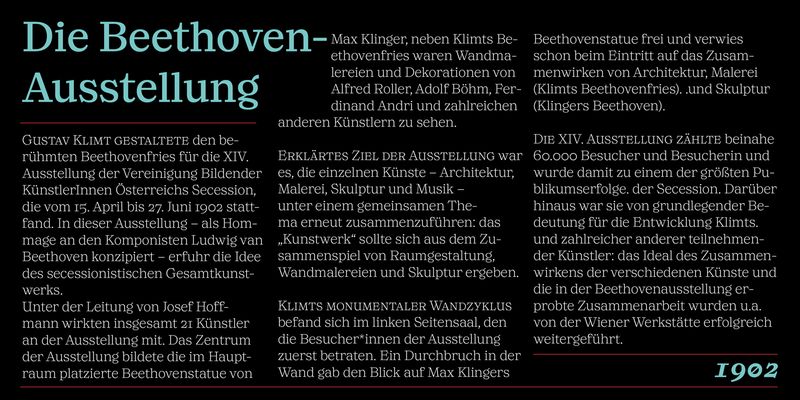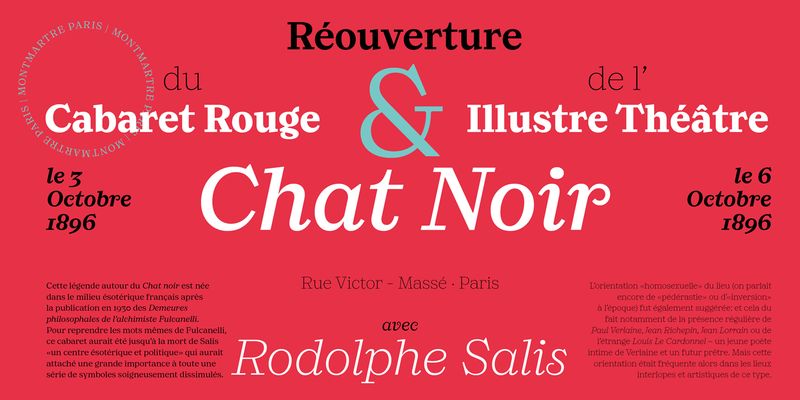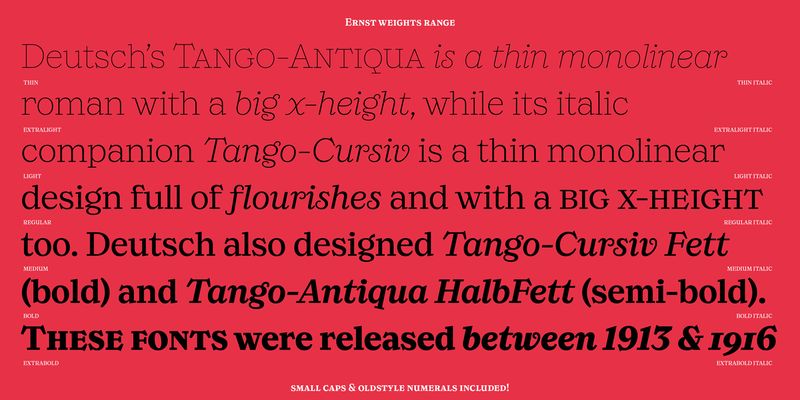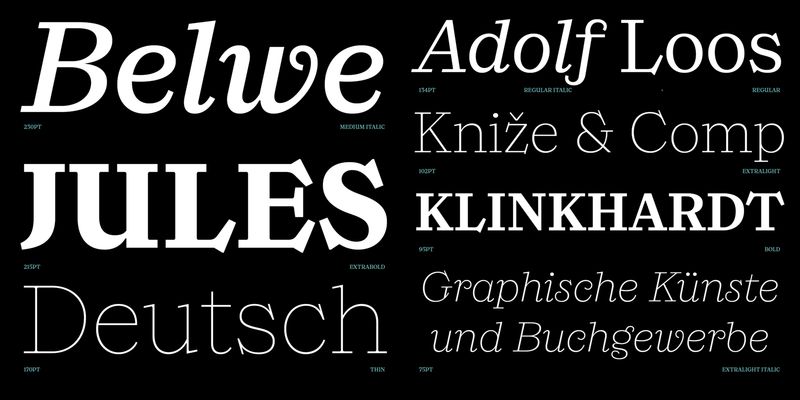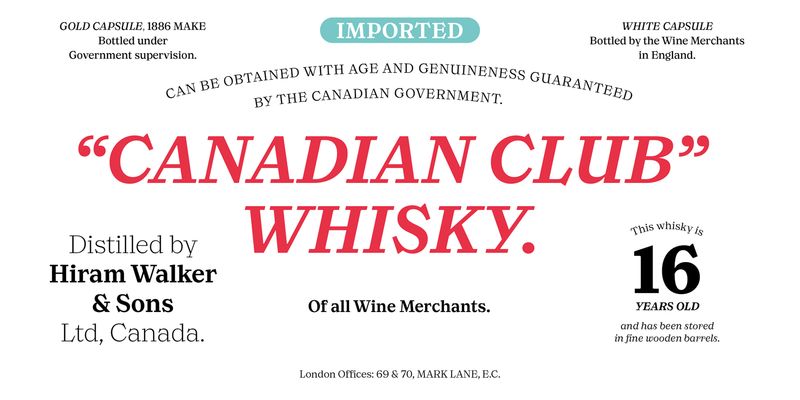
Ernst ist eine elegante, aber verspielte serifenbetonte Schrift, die an einige eigentümliche Schriften des frühen 20. Jahrhunderts erinnert, aber durch ihre breite Anwendungspalette auf zeitgenössische Anforderungen eingeht. Ernst ist weniger ein Revival, sondern verbindet Schriftdetails von Avantgarde-Schriften wie Ernst Deutsch/Drydens Tango und Georg Belwes Belwe Antiqua. Ihre ausgeprägten und verspielten Details machen sie zur ersten Wahl für Display-Arbeiten, während die große x-Höhe, ihre gestalterische Strenge und die Konsistenz der Proportionen sie auch für lange Texte geeignet machen.